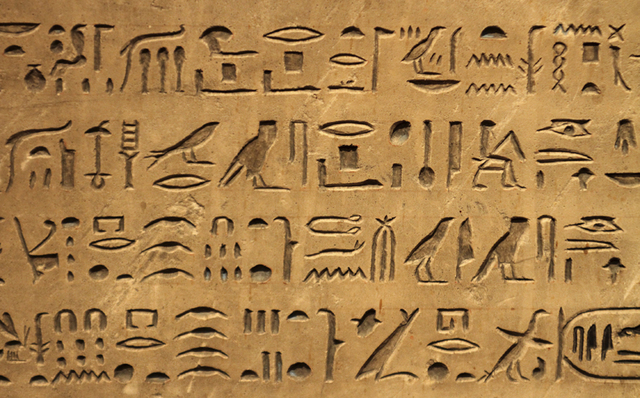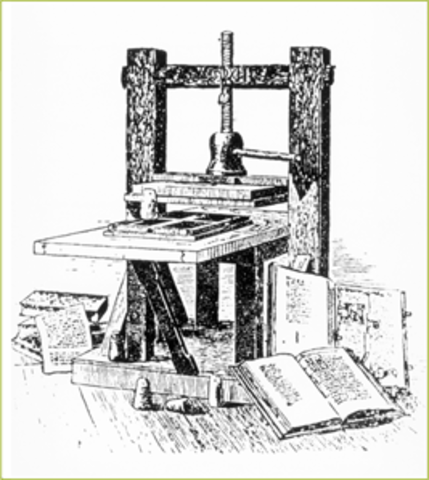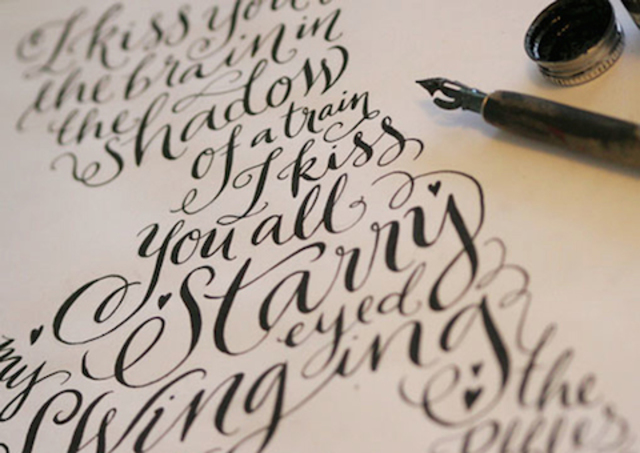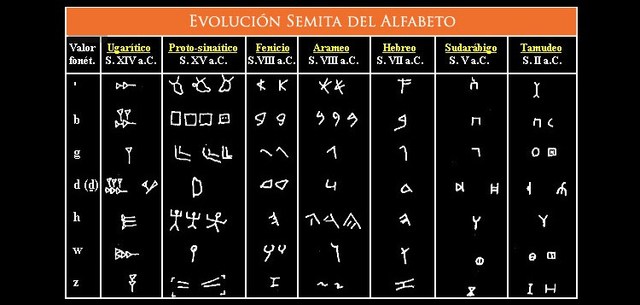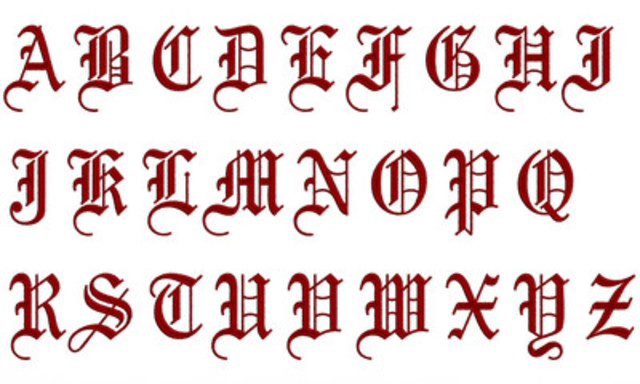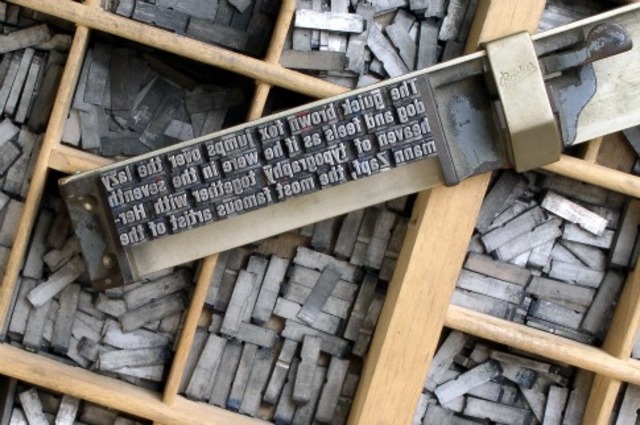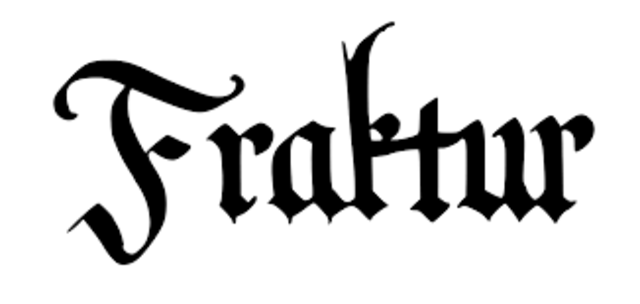
La primera escritura de la que se tienen registros surgió en la Mesopotamia en el año 4000 AC y fueron los sumerios quienes la idearon para identificar los productos en el comercio existente entre los ríos.
surgieron los Jeroglíficos egipcios (3100 AC) que fueron utilizados hasta el 394 AC.
Los asiáticos inventaron la caligrafía, el papel y la imprenta, todo esto venía forjándose desde el año 2000 AC; pero en ese entonces el oriente estaba totalmente aislado de occidente.
Arte de escribir con letra bella, artística y correctamente formada, siguiendo diferentes estilos; pero también puede entenderse como el conjunto de rasgos que caracterizan la escritura de una persona o de un documento.
La escritura cuneiforme, los jeroglíficos y la caligrafía china eran muy complejos, puesto que tenían cientos de caracteres. Para luchar contra esa dificultad surge el alfabeto, el primer alfabeto que se conoce es el semitico del Norte y surgió en lo que hoy es Siria y Palestina entre el 1700 a.C. y el 1500 a.C. Aparece como una combinación de los símbolos cuneiformes y jeroglíficos.
En el sur de Europa la costumbre en la Edad Media era utilizar la minúscula carolingia junto a las mayúsculas cuadradas romanas adaptadas de las inscripciones, como la Columna de Trajano; por tal razón, este estilo de escritura, sirvió de modelo a los primeros impresores italianos, para crear las familias tipográficas clásicas o con serifas (también llamados gavilanes o remates).
Fue usada en el Imperio de Carlomagno aproximadamente entre los siglos IX y XIII. -
En occidente el alfabeto romano fue evolucionando y, en el siglo X, en el monasterio de St. Gall, en Suiza, se desarrolló un nuevo tipo de letra comprimida y angulosa, la letra gótica, más rápida de escribir y que aprovechaba mejor el papel. La letra gótica se difundió por toda Europa, surgiendo diferentes variantes (Textura, Littera Moderna, Littera Antiqua, Minúscula de Niccoli, etc.).
Se produjo uno de los hechos más importantes para el desarrollo de la Tipografía y de la cultura humana: Johann Gutenberg (1398-1468) inventa a la vez los caracteres móviles y la prensa, creando la imprenta. El primer texto occidental impreso, la Biblia de 42 líneas de Mazarino, sale en 1.456, al parecer de la imprenta de Gutenberg.
El invento de Gutenberg había tenido tan amplia difusión, que en Europa ya existían aproximadamente 1.100 imprentas funcionando. En los países germanos el estilo de letra más usado era la fraktur (aunque el tipo utilizado en la primera Biblia de Gutenberg fue textura).
Existen multitud de familias tipográficas. Algunas de ellas tienen más de quinientos años, otras surgieron en la gran explosión creativa de los siglos XIX y XX.
Dentro de cada familia, las variables tipográficas permiten obtener diferentes soluciones de color y ritmo. Las variables constituyen alfabetos alternativos dentro de la misma familia, manteniendo un criterio de diseño que las emparenta entre sí.